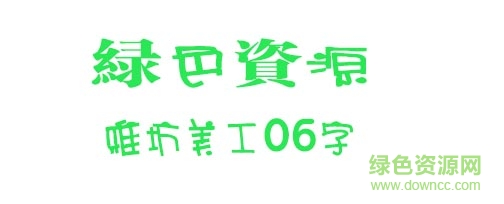
雅坊美工06
雅坊美工06是一款有点歪斜的中文字体。一般人可能用的不是很多,但是,美工朋友们就经常用到了。有需要的朋友,赶快下载体验吧!
雅坊美工06是一款用于美工设计方面的字体,该字体端庄雄秀、神韵超逸、圆融苍润,看上去十分美观,整体效果非常统一,且字库完整,可以广泛应用于美术设计、企业LOGO、宣传海报、ppt、影视制作以及内容用字等领域